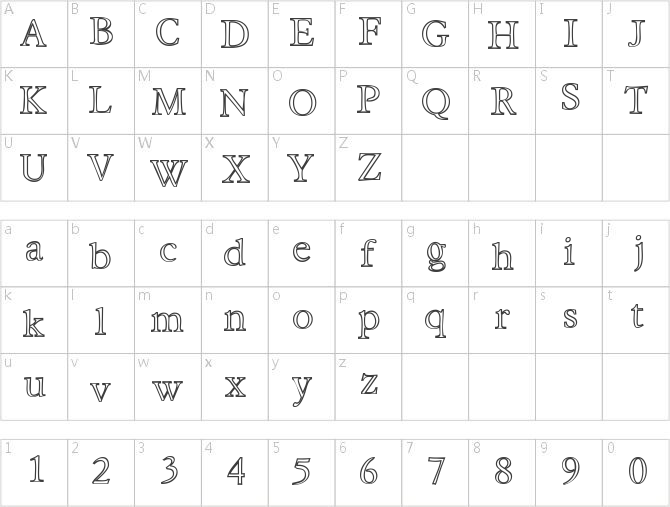
Hira & Katakana W 詳情頁(yè)
Hira & Katakana W字體字庫(kù)是一款讓人賞心悅目、百看不厭的英文字體,適合各類廣告和產(chǎn)品包裝設(shè)計(jì)應(yīng)用,字體大小0.1MB,格式為ttf字體,上傳用戶是小猴子1003,作者/版權(quán)方為未知